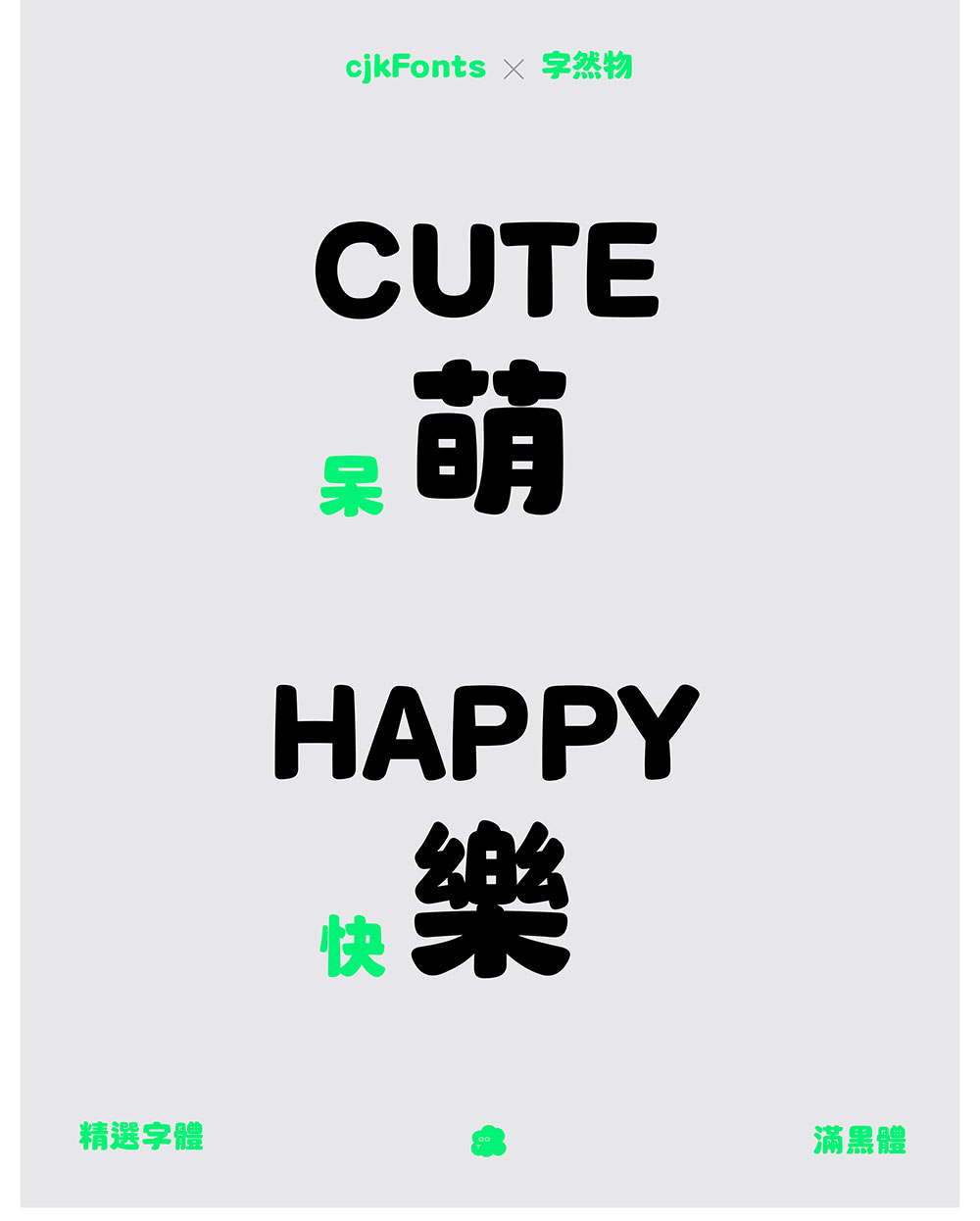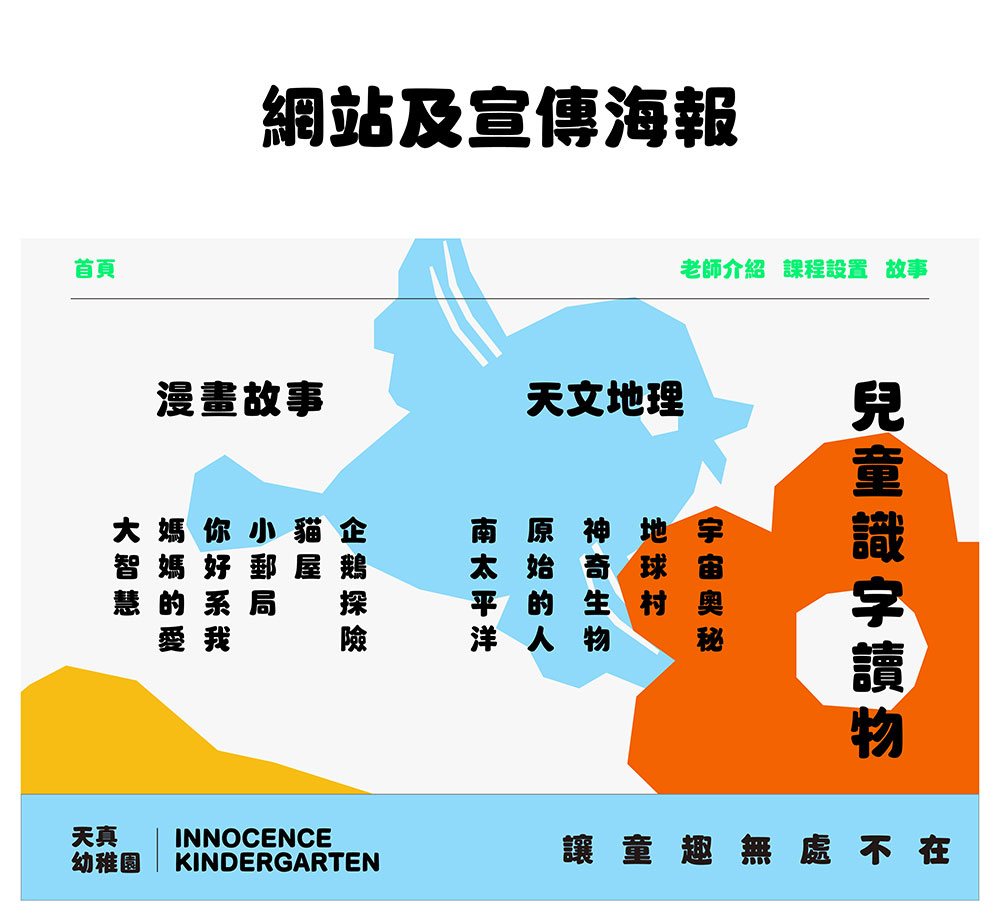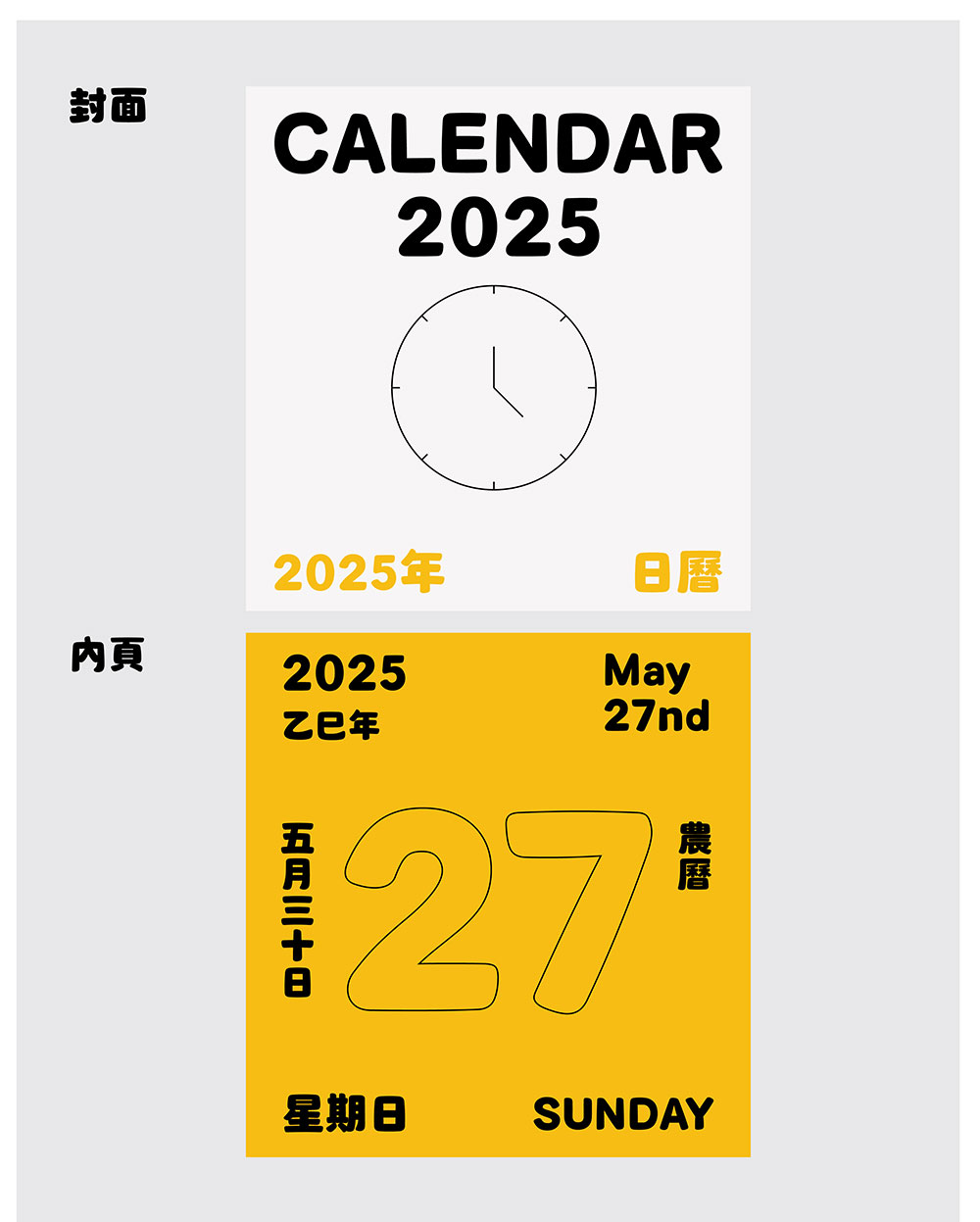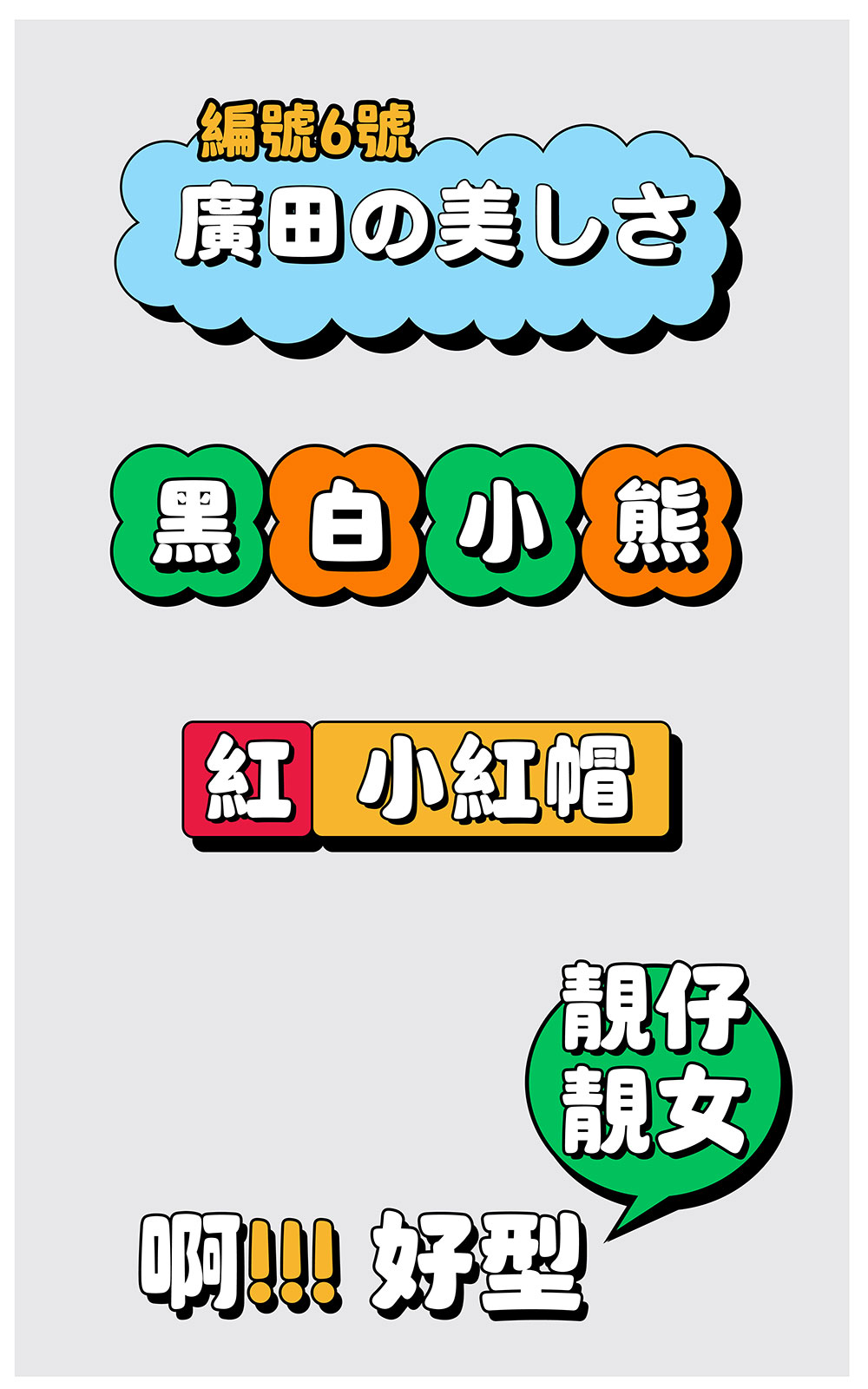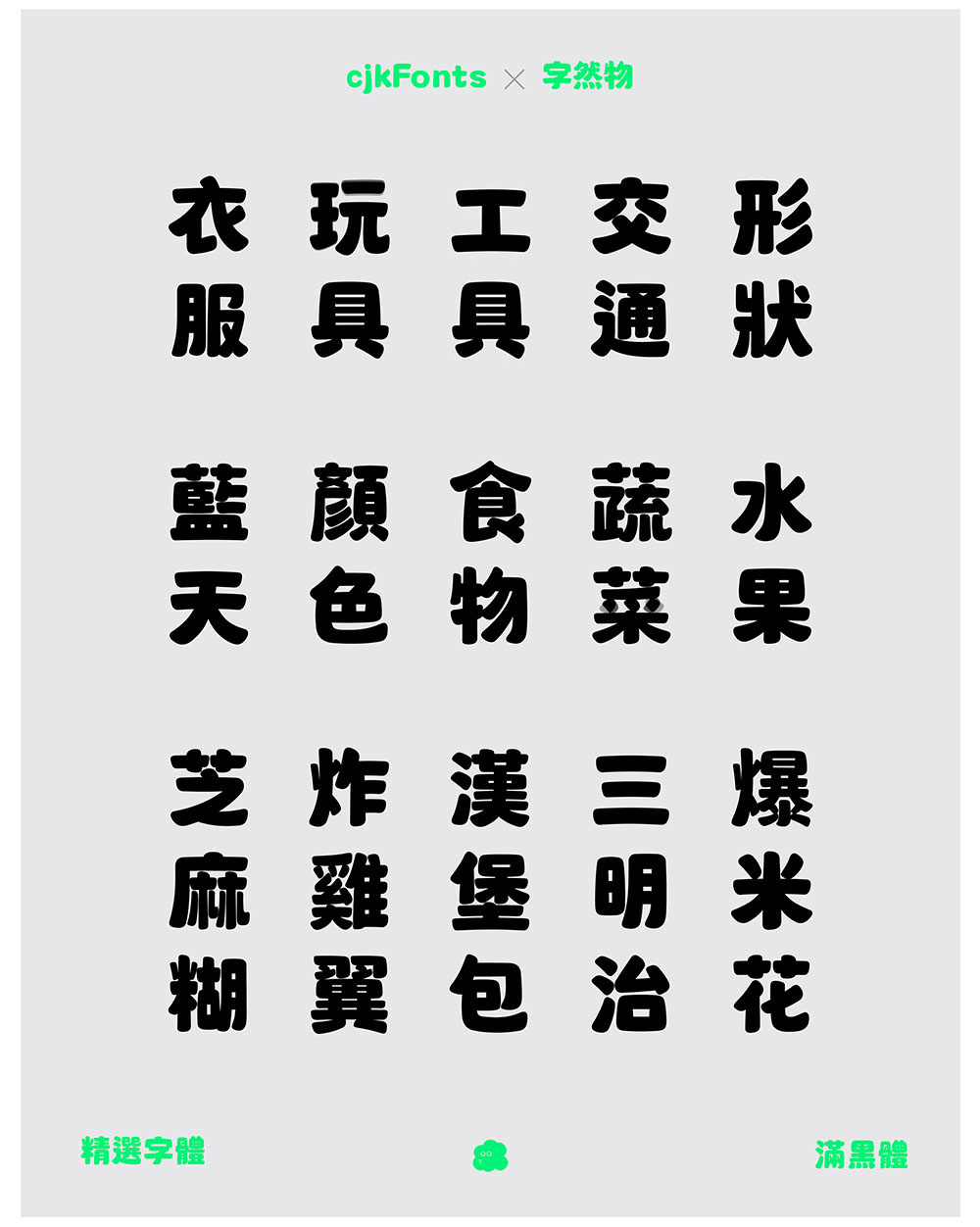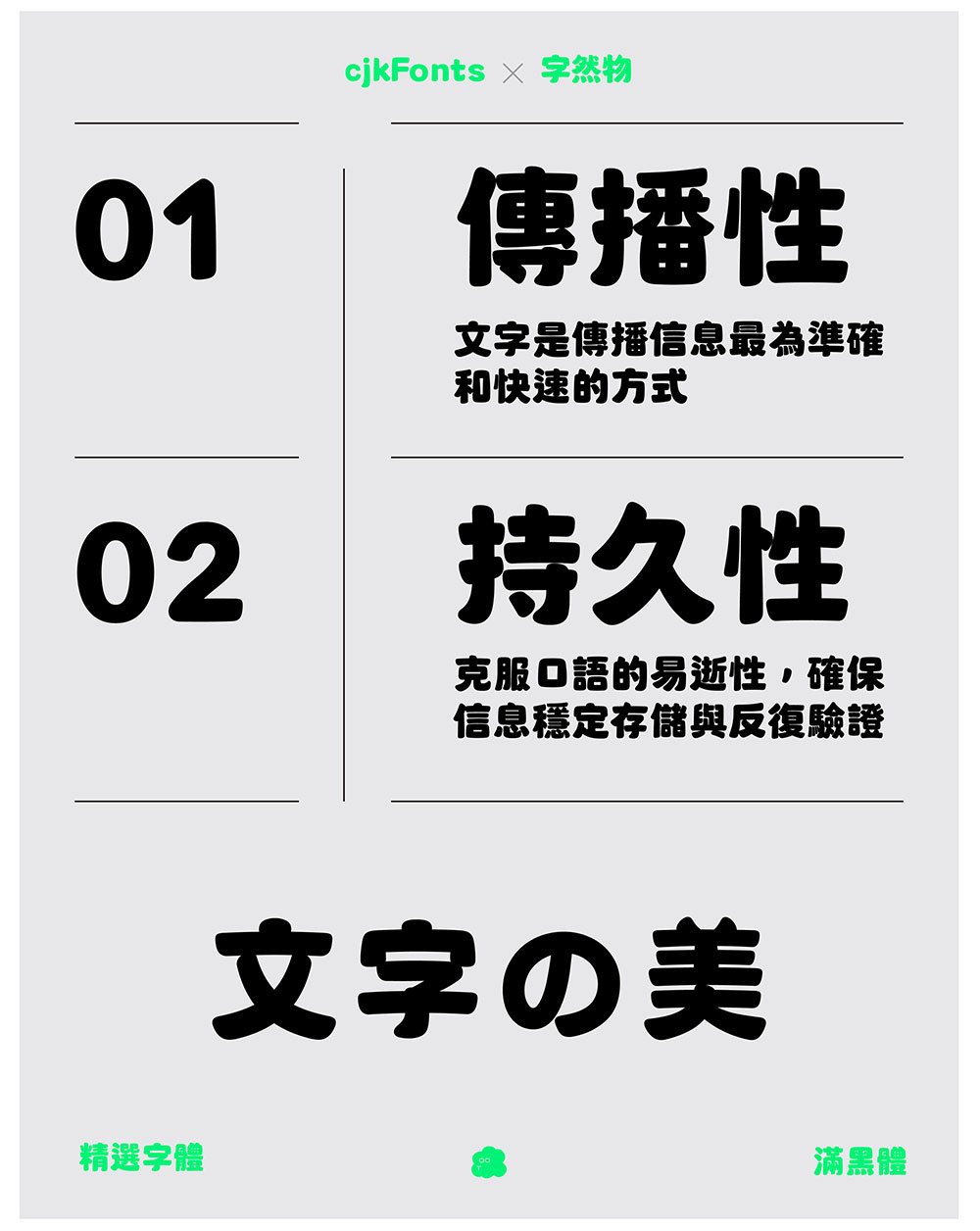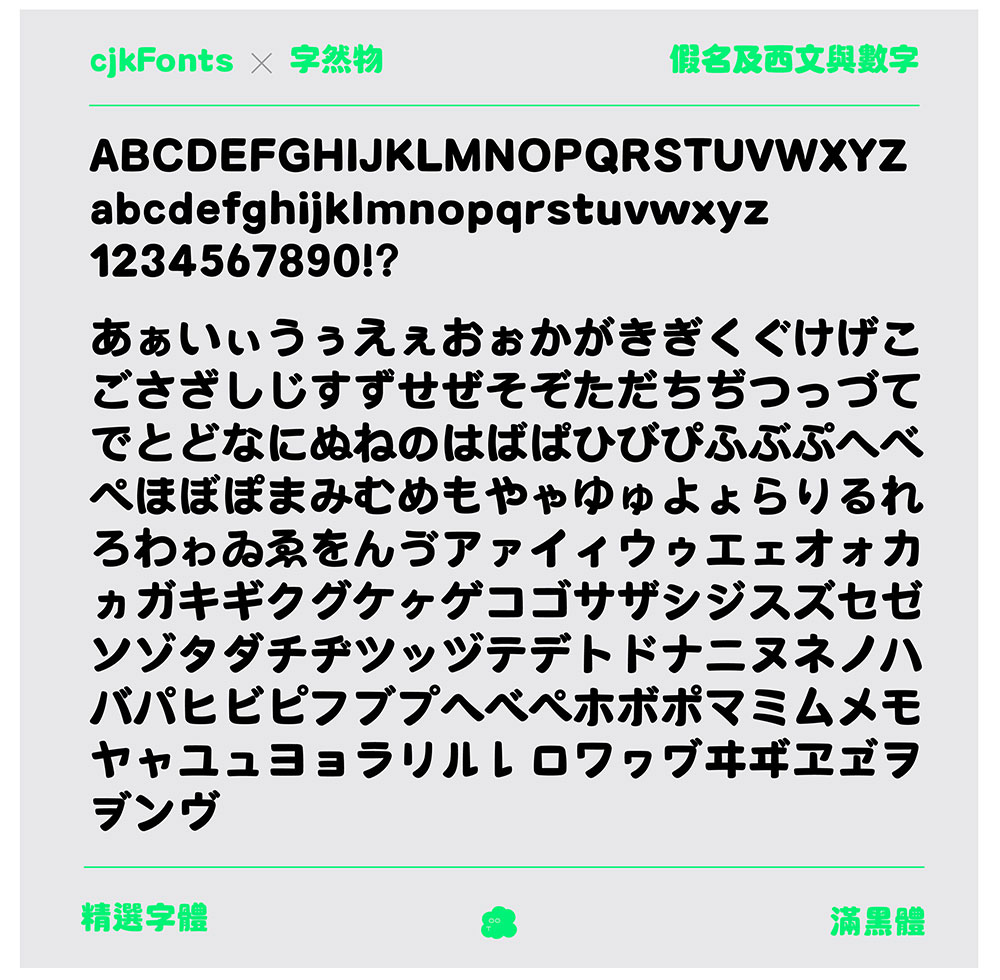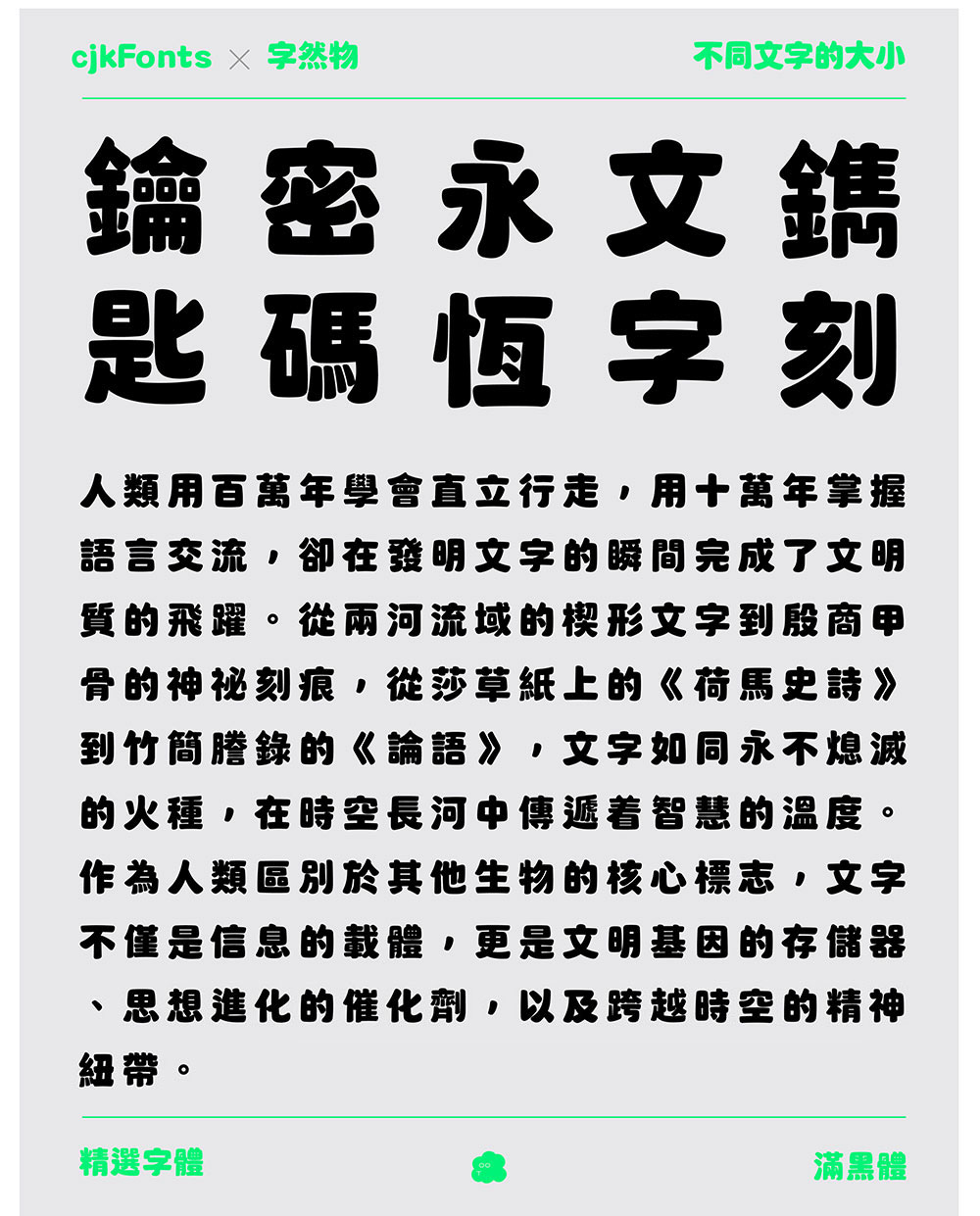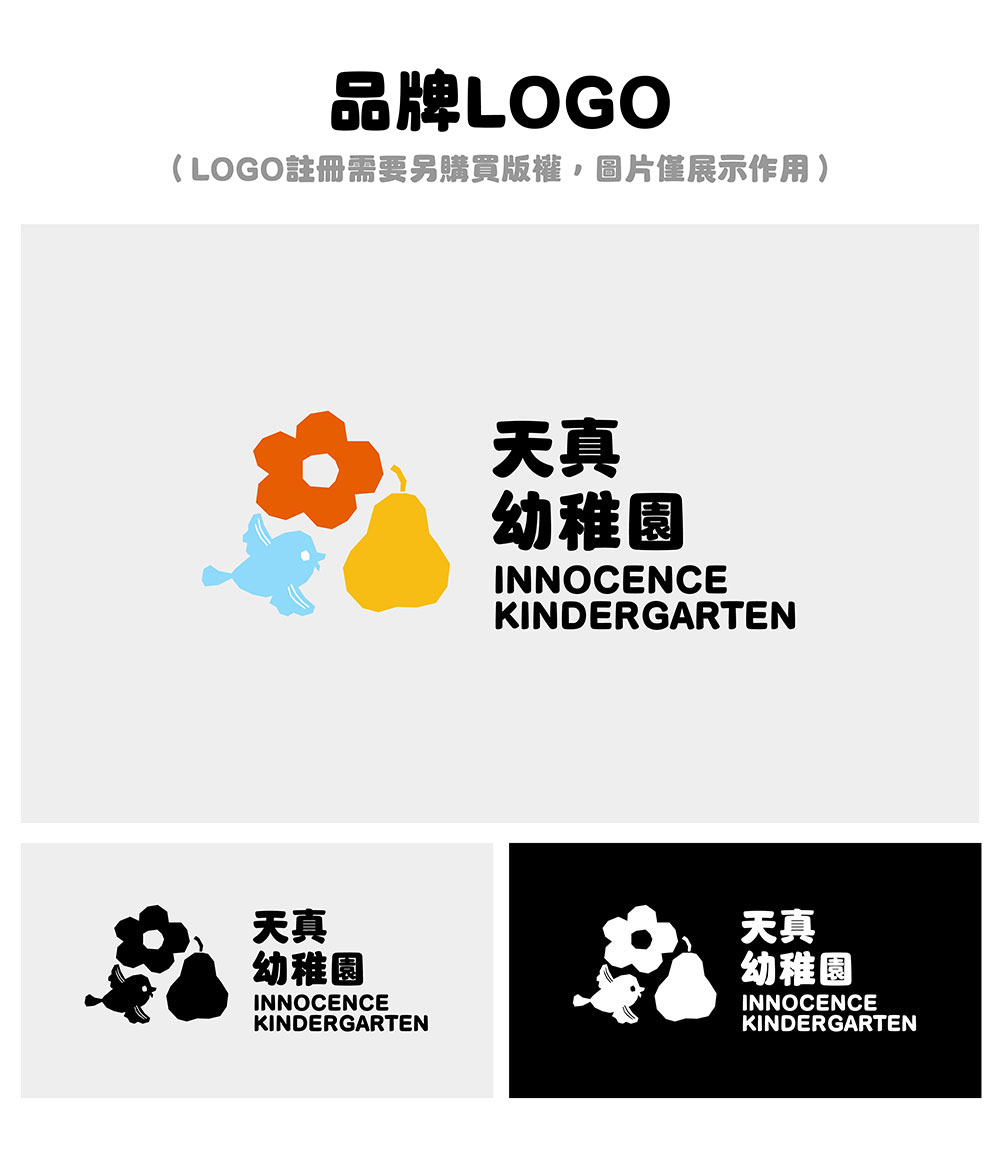
滿黑體現在大約有7900字(已新增1600字)
滿黑體 - 呆萌可愛的黑體
作爲設計師團隊在字體應用實踐中誕生的創意結晶,"滿黑體"這一命名直觀詮釋了其核心特徵——通過飽滿的幾何化字形結構傳遞獨特的視覺溫度。在字體研發過程中,我們發現市場存在顯著的審美斷層,兼具萌系親和力與適度張力的標題字體長期匱乏,常規粗體字往往因過度規整而缺乏個性表達,這正是驅動我們創作這款創新字體的動力。
在視覺表現層面,滿黑體突破傳統黑體的標準化框架,採用動態平衡設計理念。通過刻意放大的字面率與負空間優化,構建出圓潤而不失力度的字形骨架;筆畫處理上巧妙融合粗細對比與有機曲線,在確保閱讀流暢性的同時,賦予字符生動的情感張力。這種設計策略使字體既保有標題字必備的視覺衝擊力,又自然流露出適度的稚拙趣味。